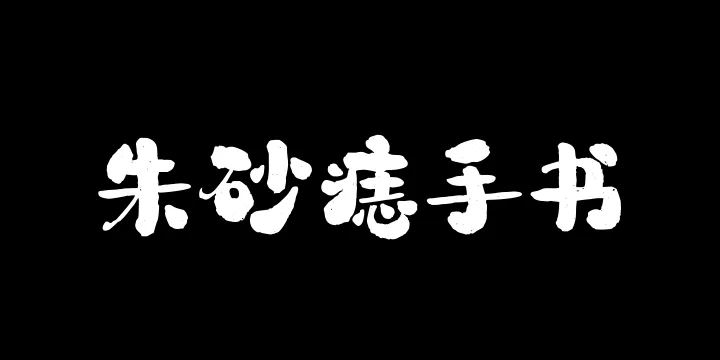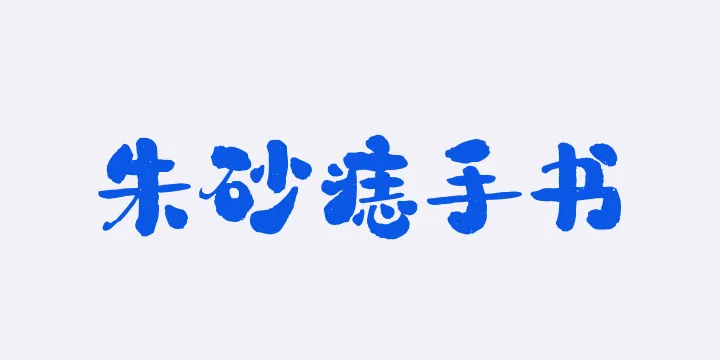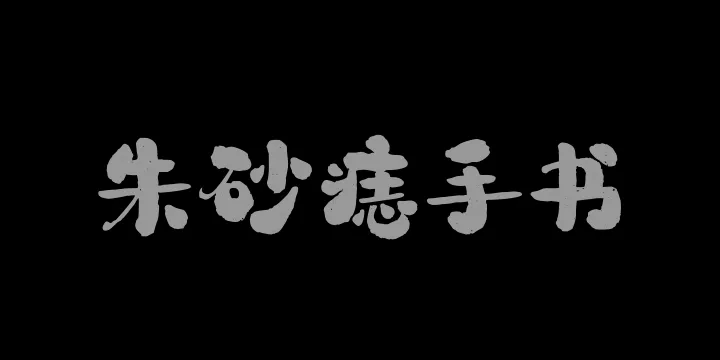
山海朱砂痣手书W By 山海字库 商用字体
关于山海朱砂痣手书W 字体字库信息
字体全名: 山海朱砂痣手书W
字体简介: 山海朱砂痣手书,是一款全新的卡通风毛笔字体,包含汉字9169个,符号200+个。该字体童趣可爱,结构多变灵动,字形活泼清新,造型生动有趣,具有灵活的适用性,天真俏皮又不失时尚感;同时以毛笔风格的表现形式,使字体更别具一格,笔画的飞白效果使字体的气息更加流畅,笔画间的关系密不可分,同时也增加了字体的自由俏皮之感。
所属分类: 毛笔字手写体